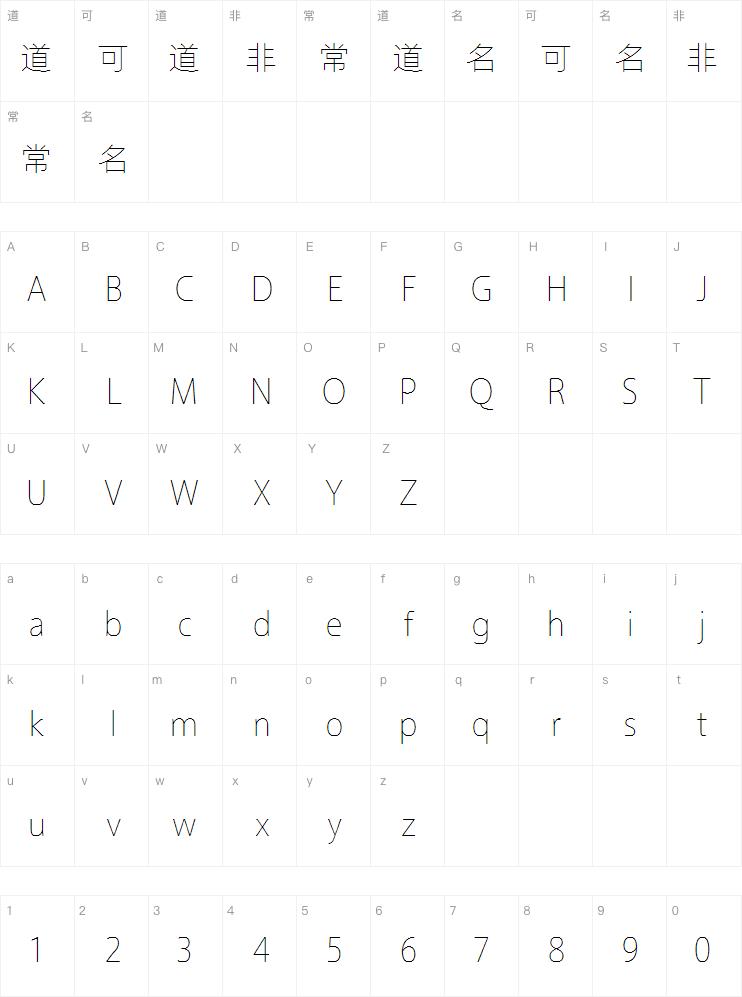
方正悠黑502L
方正悠黑家族是方正第二代中文屏显字体。其设计充分利用高清屏幕的物理特性,寻求新技术和传统审美之间的平衡;适当收紧中宫和缩小字面,使得单字的轮廓清晰,易于阅读识别。笔形保留了汉字书写的笔锋特征和间架结构,适合长时间屏幕阅读。方正悠黑家族由135款字体组成,包括15种字重,4种扁字形和4种长字形。此外,还专门设计了全套的西文字体和符号,使不同字重的西文字体在与中文混排时更加协调一致。方正悠黑的设计富含人文气息,排版清朗温润,不但适用于各种便携式屏幕,还适用于传统印刷媒介。 获奖情况:2015中国设计红星奖